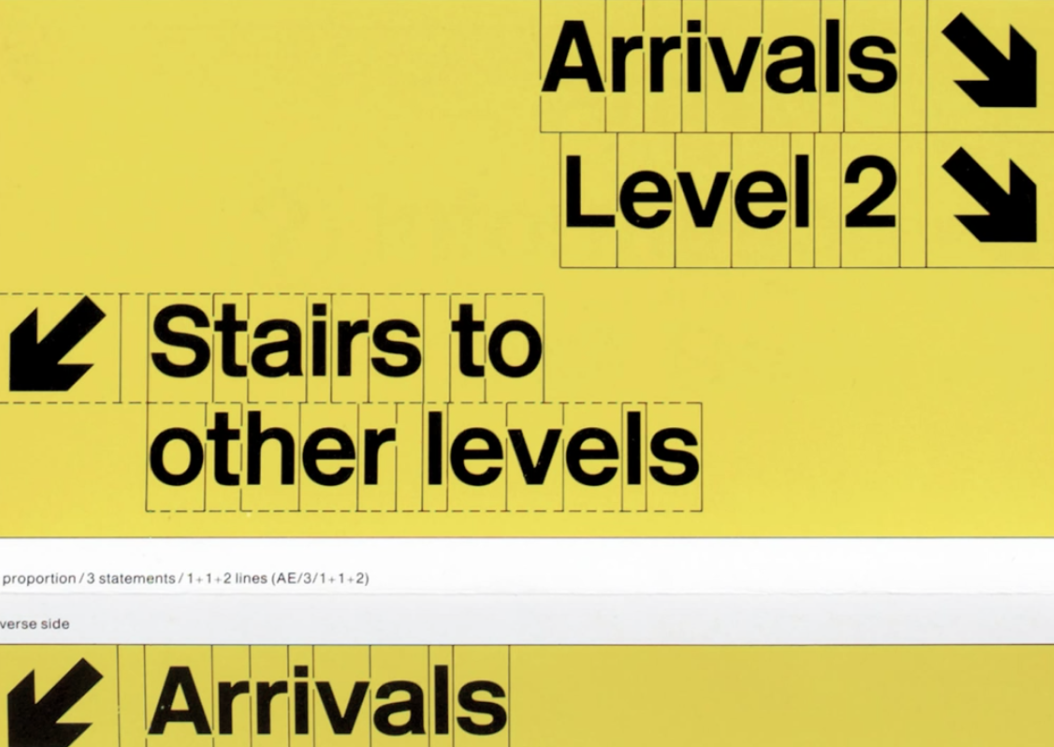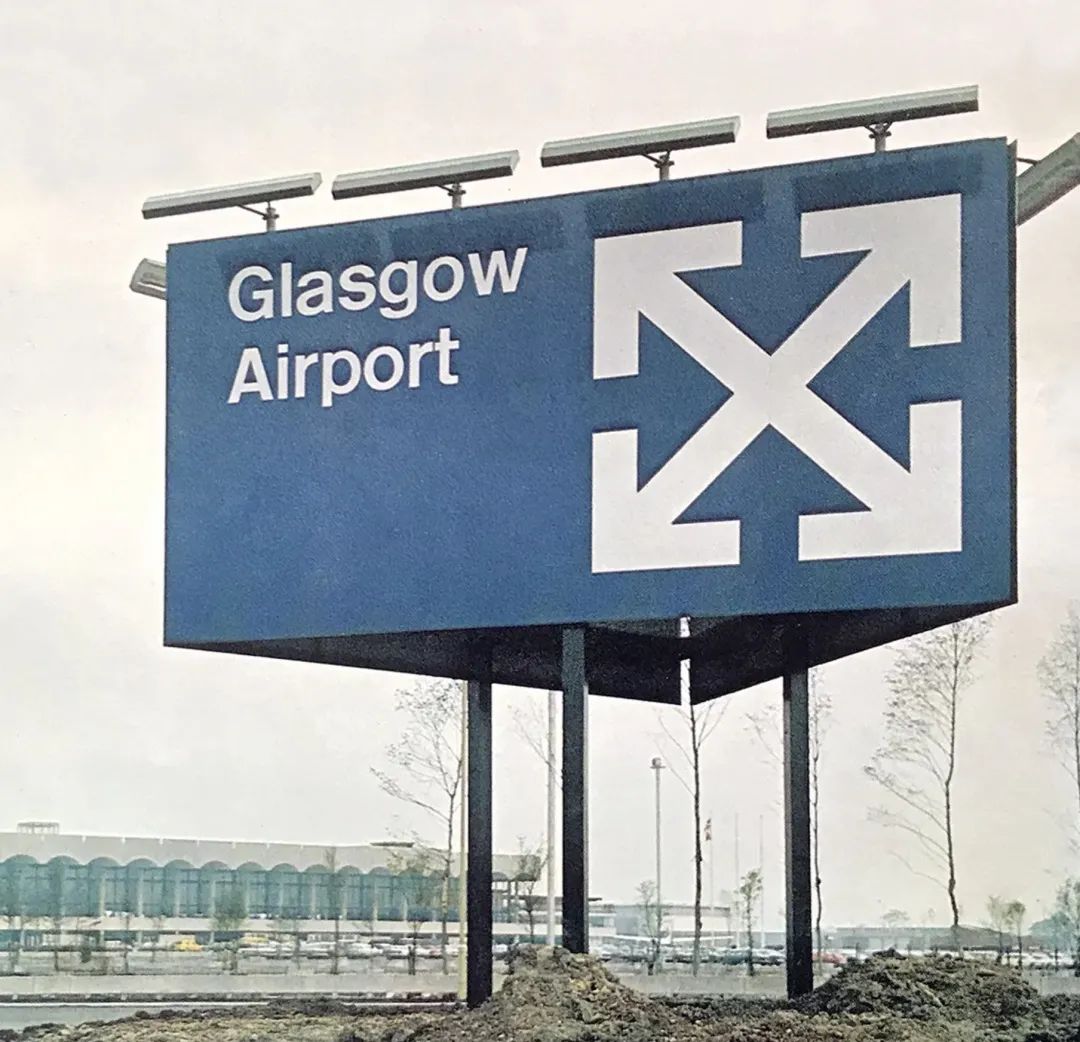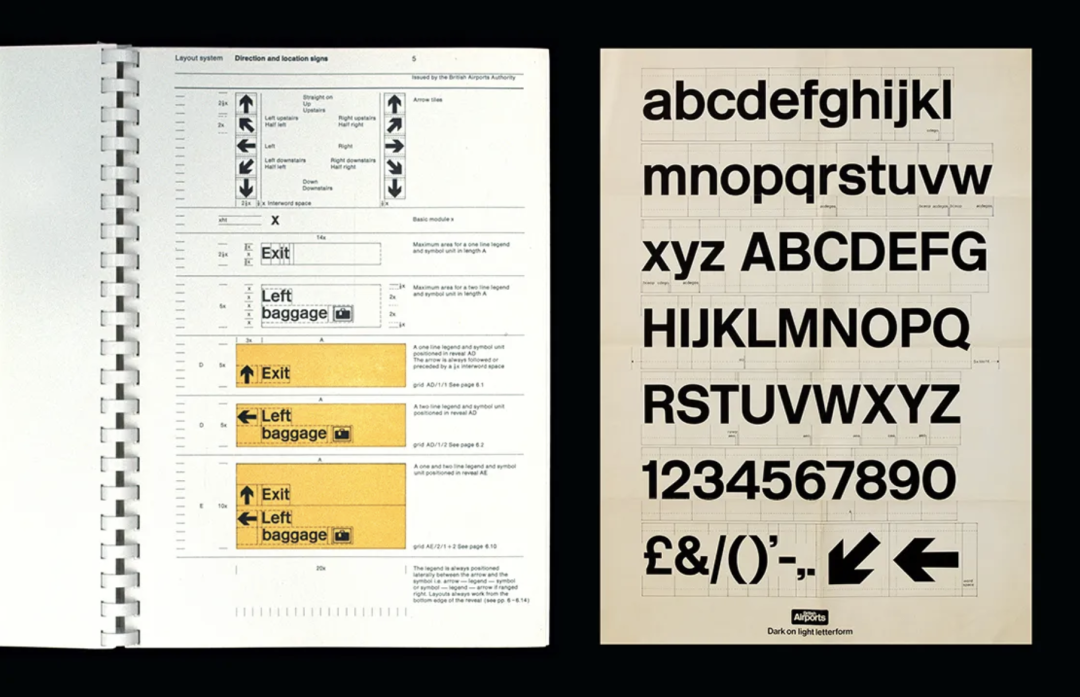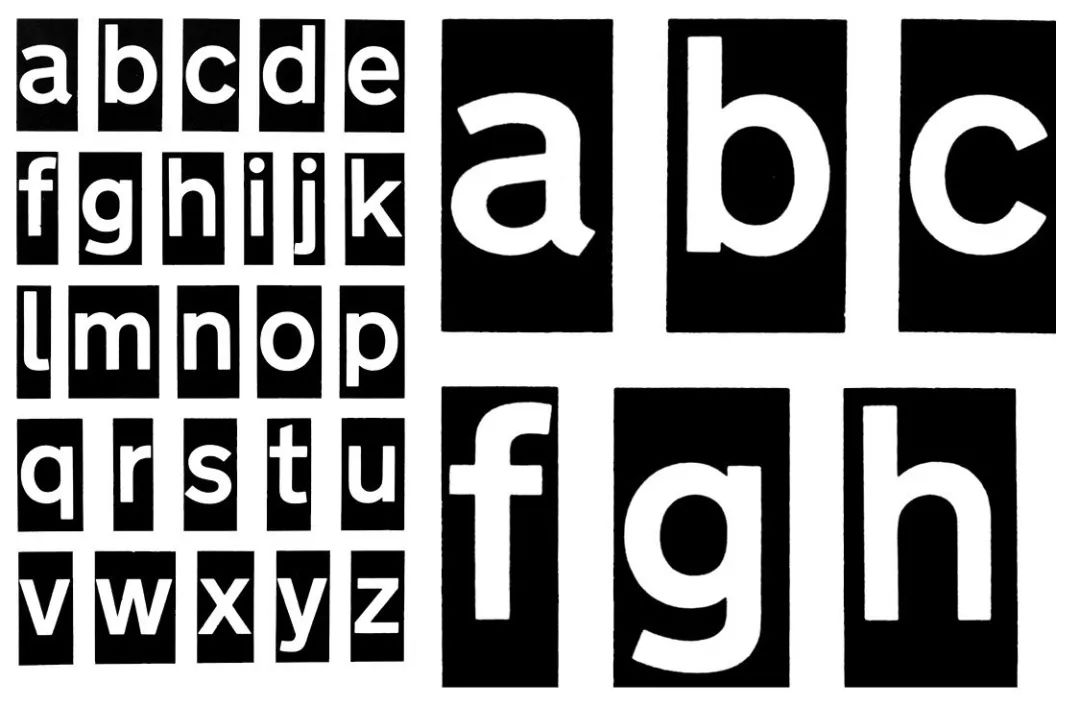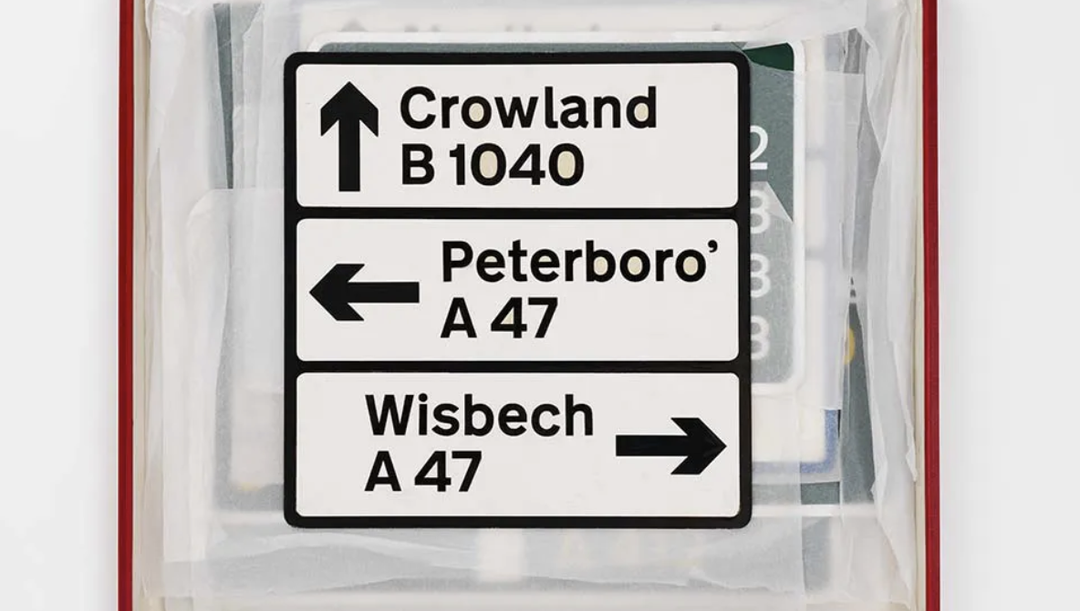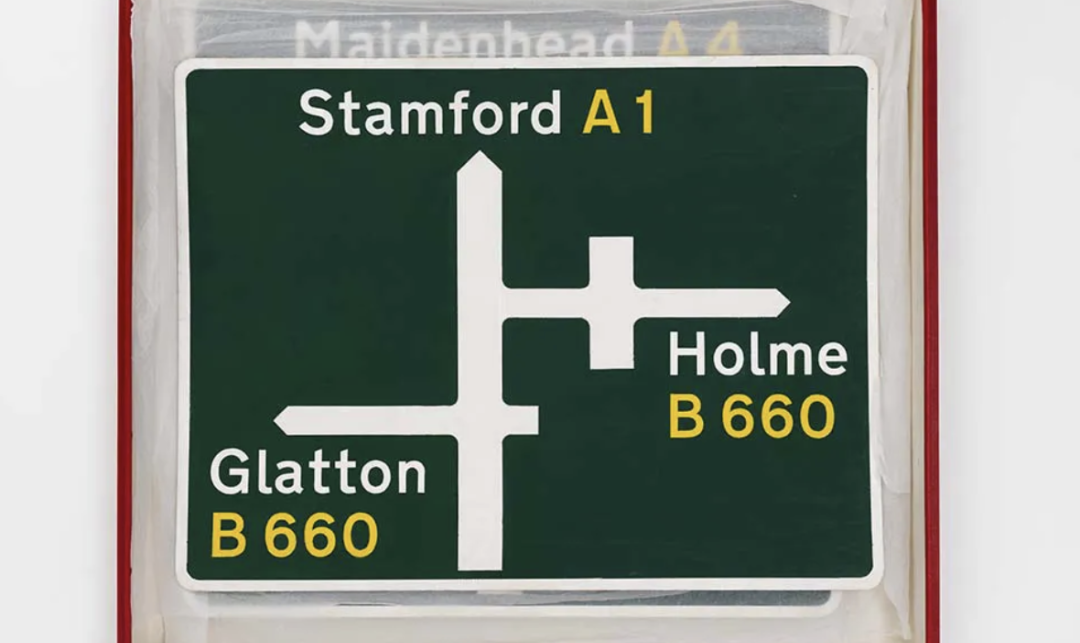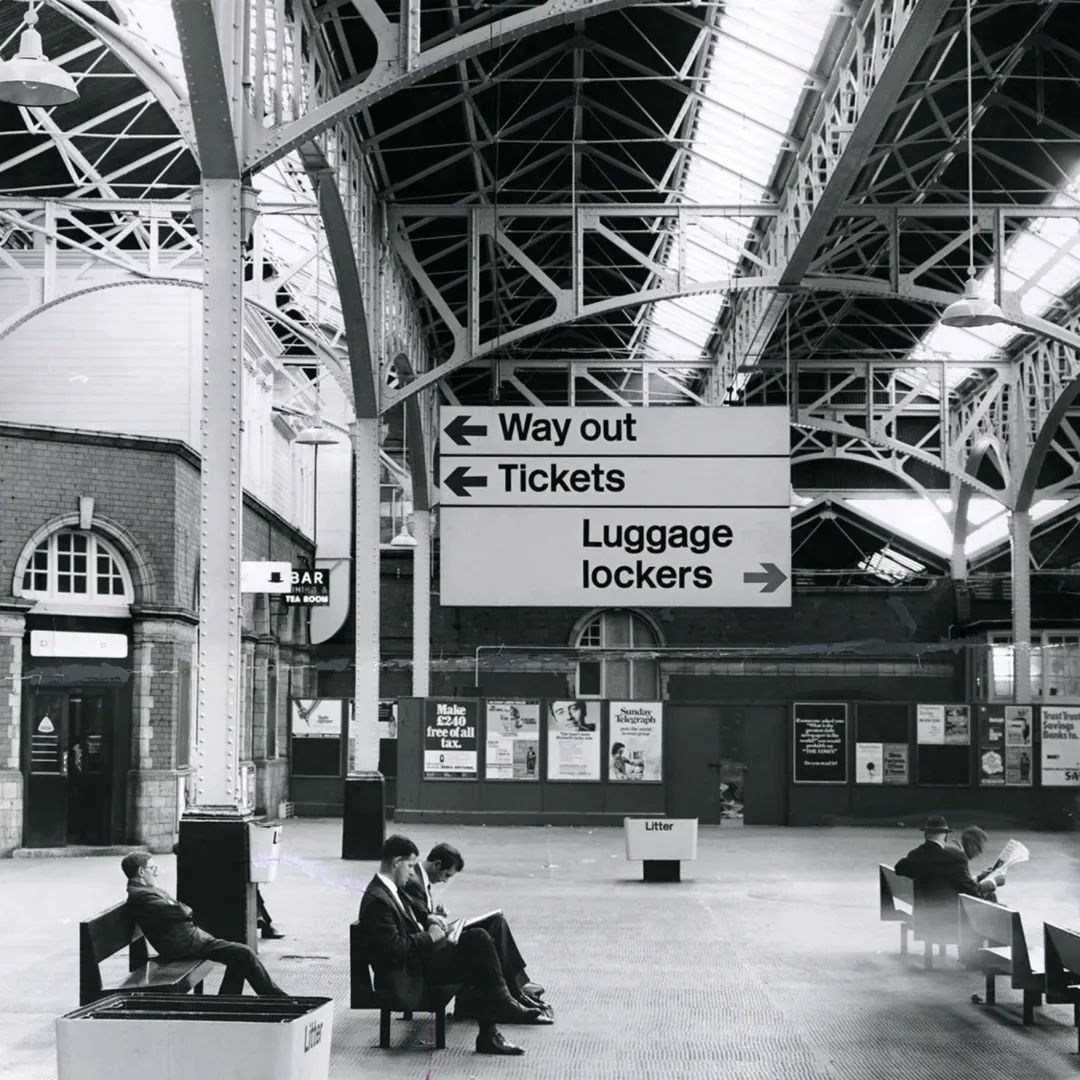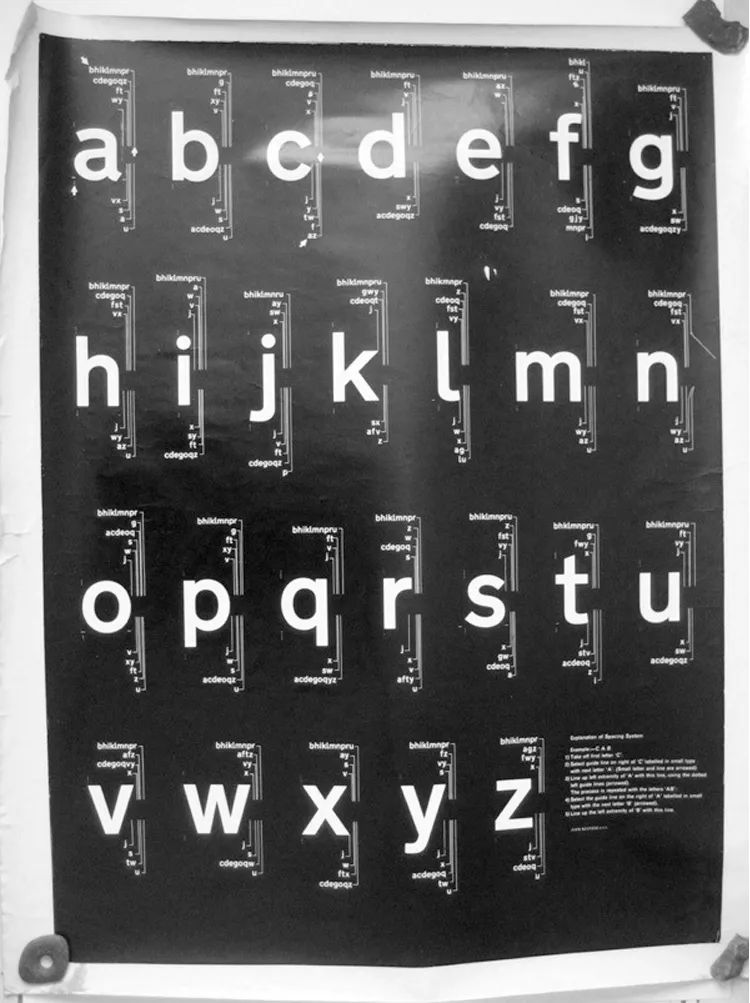
她设计的字体可能拯救了十万人的生命
它与时尚和消费无关、
与设计师个人的情感偏好无关,
只是简单地关乎逻辑、功能和解决问题。
Margaret Calvert 是视觉传达界的元老设计师。她参与了英国在上世纪中期通过交通系统字体革新推动社会进步的典范设计。在20世纪50年代到60年代之间,她与 Jock Kinneir 共同为英国的公路、铁路与机场创造了统一的交通标识体系,宗旨和原则至今依然启发着全球的导向设计界。今年已经84岁高龄的她,最近为翻修后的英国轨道网络系统又一次绘制了自己曾经创造的“铁路字母表”,卷宗邀请了伦敦设计博物馆前馆长 Deyan Sudjic 对她进行了采访。
上图:英国交通信息系统的字体创造者、平面设计师 Margaret Calvert
下图:Margaret 为交通系统设计的经典标识
切尔西艺术学院的教授 Jock Kinneir(左)把 Margaret Calvert(右)招纳进了自己的工作团队,师生两人共同完成了英国交通标识的更新设计。
我更愿意成为解决问题的人,
设计是一种服务,
应该具有普遍性。
每一位英国人和到访英国的游客,都曾经在某个时候看过或接触过 Margaret Calvert 的作品。20世纪50至60年代间,战后英国的道路交通建设工程开始如火如荼地扩张。在这样现实背景下,重新设计路标和字体的任务已经迫在眉睫,Margaret Calvert 和 Jock Kinneir 两人合作完成了英国的交通标识与字体的更新工作,这也是当时英国历史上最大规模的设计项目。
上图:格拉斯哥机场的户外标牌
下图:希思罗机场标识图
这项庞大的设计工作包括整合并提出一套全新的交通视觉语言设计体系,例如将大写字母转为简洁而独特的小写字母、创作圆滑而现代的新字体、特定的颜色代码等一系列细节的变化。更新后的字体可以在高速移动的过程中被轻松阅读,标牌的内涵能够在极短的时间之内在驾驶员的大脑中被处理并理解。据统计,由于字体革新而免于发生的交通事故,相当于约能够挽救数十万英国人的生命。
Calvert 设计出了统一的字母表 Rail Alphabet,这也是当时的英国铁路公司(British Rail)所要呈现的新面貌的一部分,此外还包括 Design Research Unit 为其设计的双箭头标志。这个项目更大的目标,是重振英国铁路系统的使命感和公共责任感。
除了在机场、公路和铁路的途中,Calvert 和 Kinneir共同设计过的各种字体还出现在了当年英国野兽派建筑风格的医院,在各种公共场景为人们提供引导。这项革命性的项目随后成为了现代道路标志设计的典范,并在全世界范围内得到推广。
1958年至1965年之间,他们在完成了对于航空和铁路的设计更新后,开始接受英国的所有道路标志设计的任务。
据 Calvert 回忆,当时的设计院校并未专门开设平面设计专业,这一领域通常被称为“商业艺术”(Commercial Art)。但是这一大型设计项目则具有强烈的公共性,与时尚和消费无关、与设计师个人的情感偏好无关,它只是简单地关乎逻辑、功能和解决问题。“我不想成为一个在阁楼上自我挣扎的插画家。我更愿意成为解决问题的人,设计是一种服务,应该具有普遍性。”Calvert 曾经表示。
Calvert 和 Kinneir 根据交规体系设计的一套道路交通标识
不仅是字体,Calvert 和 Kinneir 还根据交规体系设计了一整套路标的图形规范:三角形提示警告,圆形代表说明,矩形交代信息。令人愉悦的箭头,清晰而明快地指示着每一位交通参与者。一只在红色圆圈中奔跑的鹿,警示前方道路可能会有野生动物出没。临近学校的公路上设置提示经常有孩童出现的牌子,Calvert 把曾经的标识上由“小男孩拉着小女孩过马路”的标识改为了如今的“小女孩带领小男孩”。
Calvert 和 Kinneir 的字体
这些交通标识集大成地代表英国设计界的水平,作为一道醒目的存在,已经成为了社会视觉景观中的有机组成部分。有人称 Calvert 和 Kinneir 的字体与标识设计就像是设计师成为脑外科医生,把交通信息的传达和接收过程改善为高效的通路。
这就像是手工编织一样,
创作字符的方法就是亲手绘制出一切。
Calvert 的工作台与“Women at Work”标识
Margaret Calvert 的工作台是一块老式平行运动制图板,上面堆放着大量的素描和速写,使它几乎隐匿在了起居室的角落里。在制图板上方,Mark Rothko 的明信片旁边,放着一块缩小版的蓝色高速公路标识牌,上面标出的是英国 M1高速公路邓斯特布尔(Dunstable)的拐弯处。
Calvert 设计字体时的铅笔创作手稿
工作台右上方的墙上贴着她创作的一幅铅笔画,醒目的红色三角形中框着一名穿裙子的女性工人。这件标识“Women at Work”(“工作中的女人”),下面注着一行小字“Woman having difficulty with large umbrella”(“一个正在努力撑起大伞的女人”)。这是她对自己当年设计的“Men at Work”警示标识的一种趣味颠覆,后者已经成为提示道路施工现场的通用标志。Calvert 甚至曾经把这个版本称为她的“自画像”。
火车站内的标识系统
如今,英国铁路私有化之后所带来的一系列问题使改革迫在眉睫。英国铁路现在的所有者英国铁路网(Network Rail)已经对伦敦的主要车站进行了改造,目前正在着力解决图形标识不一致的问题。为了匡正铁路私有化过程中所制造的视觉混乱,他们的顾问建议重新采用当年的字体 Rail Alphabet。但是,Calvert 给出的方案则是重新设计一套新的字体。在完成了这套新字体的创作后,字体设计师 Henrik Kubel 又将她的手稿进行了数字化处理。
Calvert 去年创作的新版 Rail Alphabet 2手绘稿
英国铁路网(Network Rail)提出的要求是为新的字体制定出两种粗细程度,包括所有26个字母的大小写形式,以及数字、符号和方向箭头。“小写字母’a’是引出其他所有字符的关键字,”Calvert 说道。她坦言自己对大写字母从来都没有特别感兴趣。她会徒手画出每个字母的轮廓,然后再花上几个小时用黑色软铅笔填补每个字母的主体部分。这是一项费时又费力的工作,但整个过程又是必不可少的。这给了她足够的时间去思考每一个字母,并为其赋予一种独特的字符形态。“这就像是手工编织一样,”她说,“创作字符的方法就是亲手绘制出一切”。
上图:Calvert 设计的第一套 Rail Alphabet 字体
中图:Gill Sans 字体
下图:Neue Haas Grotesk 字体
Calvert 介绍说,“第一套 Rail Alphabet 字体的灵感是在1960年获得的,当时到处都在使用 Gill Sans 字体,但我自己从来都不喜欢这种字体。后来,Neue Haas Grotesk 字体突然问世了。”她提到的这种字体还有一个更广为人知的名字——Helvetica,是由瑞士设计师 Max Miedinger 在1957年设计的。因此,Calvert 当时所设计的字体可以说是在看到 Helvetica 之后的一种反应;并非是简单复制,而是提出了一种全新的用法。
Margaret Calvert 为伦敦设计博物馆30周年纪念展所设计的路标,将于今年年底展出。此前,伦敦设计博物馆邀请了30位艺术家和设计师以字“30”为主题开展自由创作
如今,这套新字体的各个细节完全是由她自己决定的,包括所有的曲线和间距,甚至是小写字母“i”上的圆点。“设计师不应该随波逐流,而是要主动寻求灵感,”Calvert 谈论了自己设计生涯的创作心得。“我不喜欢被定位成一个排版设计者;他们总是会过度关注字体的整洁程度,因而忽略了一种字体是如何产生的,”她表示,“我现在的工作状态很舒服。最关键的是,要找到属于你自己的路。”